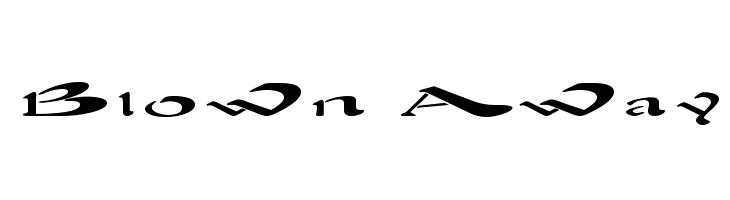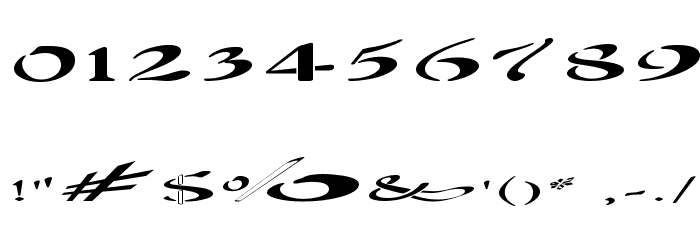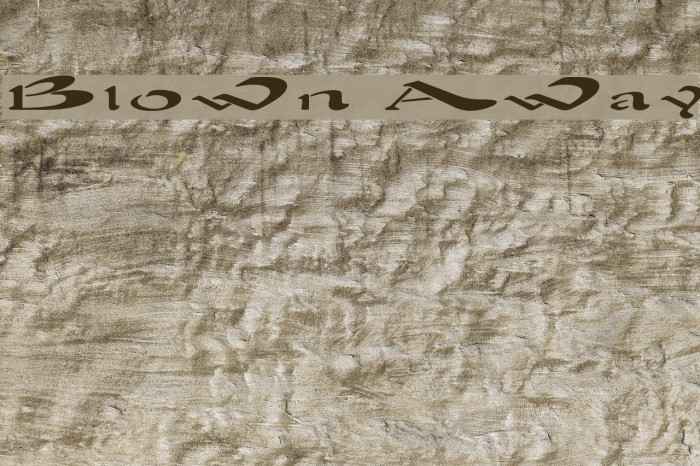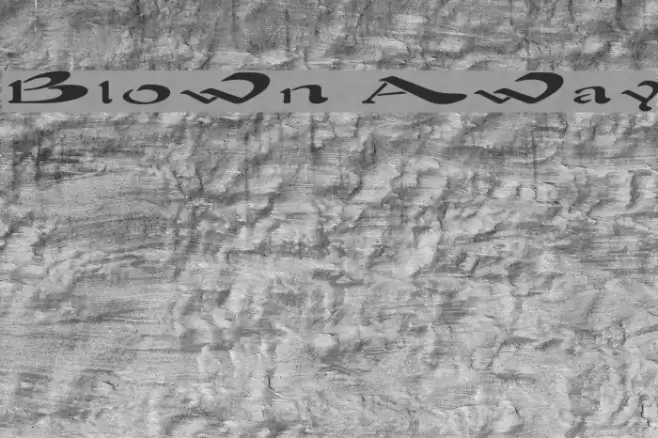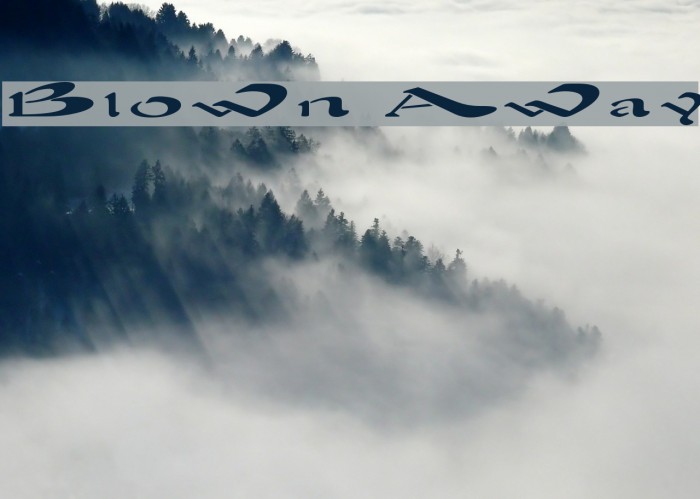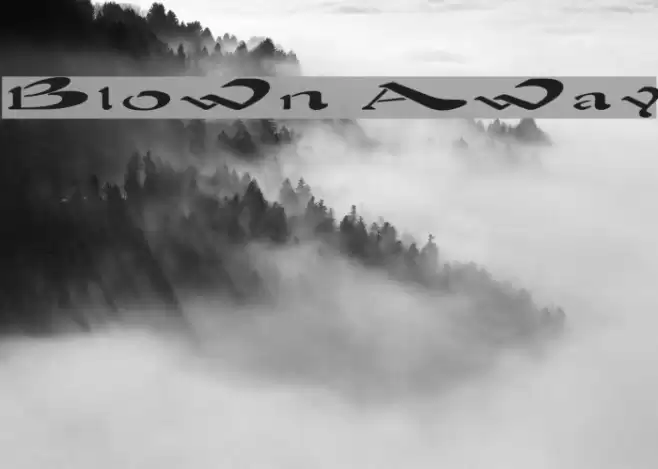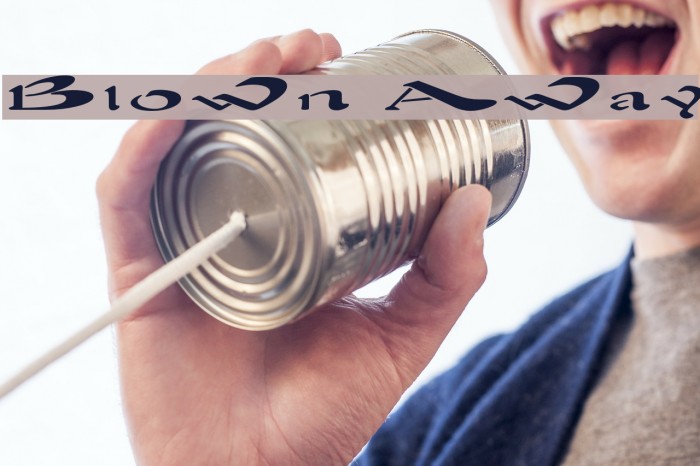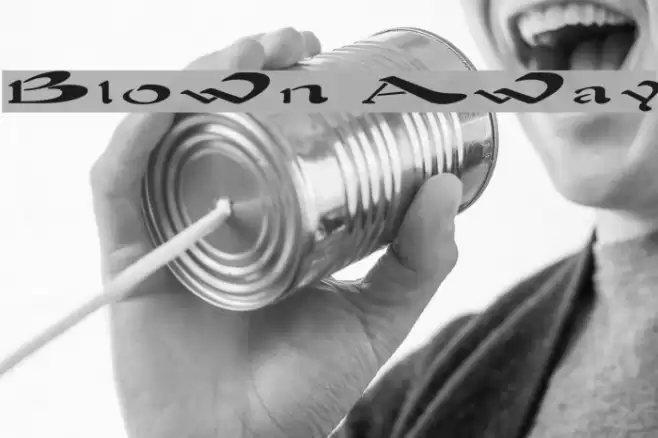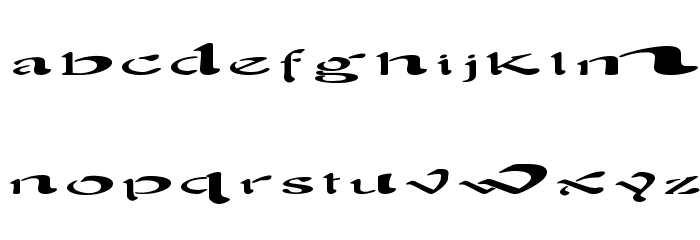
Blown Away Font
✎ Quirky
| Categorías | Quirky |
| Estilo general | Artistic and expressive |
| Caso de uso | Logos, headlines, artistic projects |
| Proyectos propuestos | Ideal for creative projects such as branding, invitations, posters, and artistic designs. |